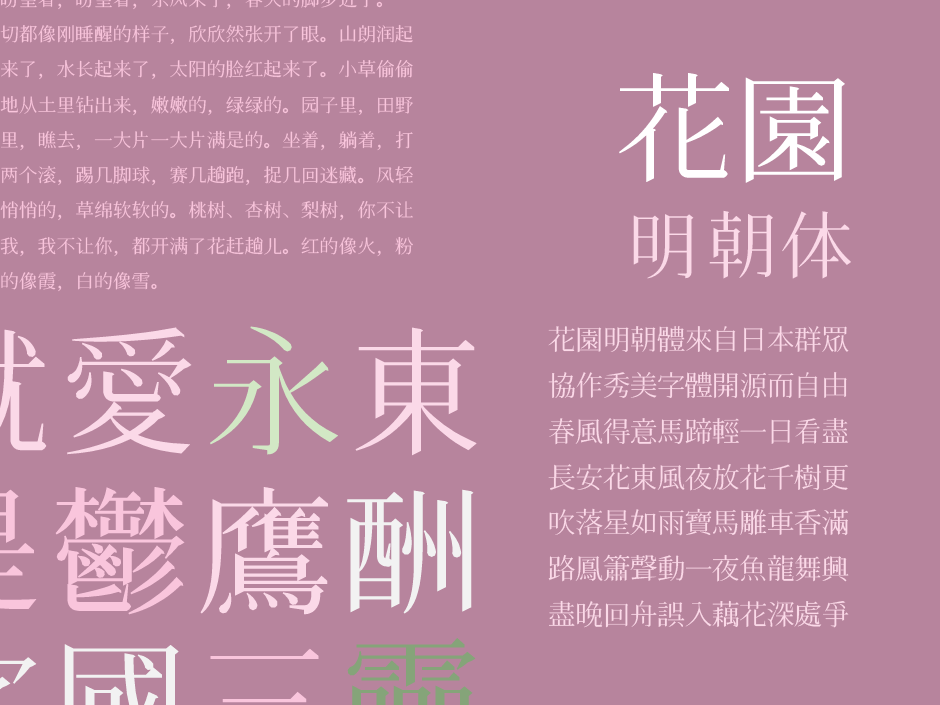
花园明朝体(花園フォントについて)
一款基于日语的自由开源汉字字体,也是 GlyphWiki Project 的一部分。这款字体的特点是涵盖了目前 CJK (中日韩统一表意文字)字库中几乎所有的汉字与字符, 而且作为开源项目,任何人可自由下载使用。
「花园明朝 」 是一款免费字体,为 GlyphWiki 所开发,字形数量共 45090 + 47186 个,几乎收录了所有汉字字形。缺点是字形以日本字形为准,有一些字不符合中文书写规范。